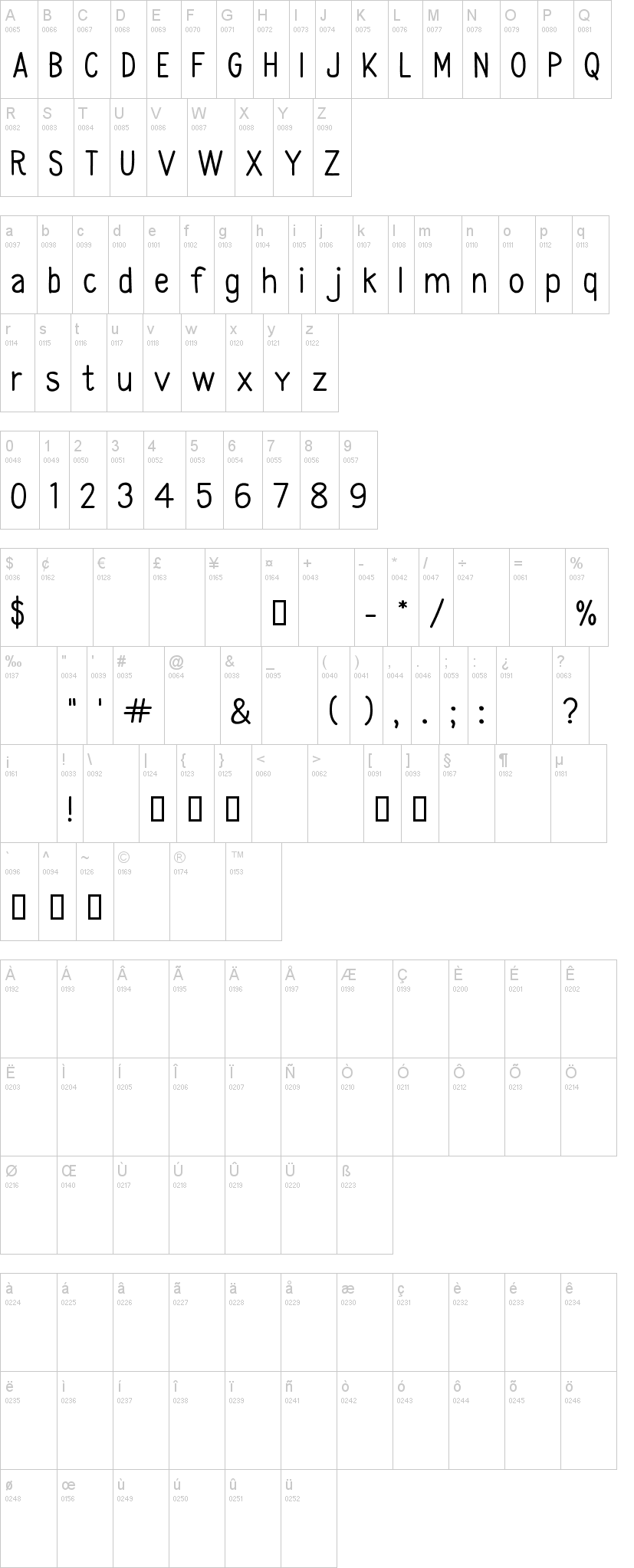
CF Second Son
CF Second Son 字体是一种免费的手写风格字体,由北京的设计师 YoonDesign 开发。这个字体的风格非常独特,看起来像是一个有才华的艺术家或音乐家会使用的手写笔迹。 CF Second Son 字体在设计上非常注重细节,每个字母和符号都有自己特定的风格。这种字体可以用于海报、广告、标志、网站等各种设计项目。由于它具有很高的可读性和美学价值,因此在许多设计师和艺术家中都很受欢迎。 CF Second Son 字体包含大写字母、小写字母、数字和标点符号,可在多种平台和软件中使用,如Adobe Photoshop、Illustrator、Sketch、Figma等。此外,该字体是免费的,可以在许多字体网站上下载和使用。
CF Second Son是一款非常不错的手写艺术字体,具有很好的视觉感,适合于文化类的宣传设计、商业类品牌的广告和产品包装设计以及个性化文字排版等较多场景。